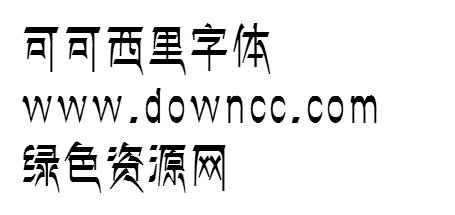
可可西里字體是在可可西里影視中較常見到的一款藏文字體,中英文都有著不錯的藝術(shù)風(fēng)格,造型精簡而獨具地域風(fēng)情,快來綠色資源網(wǎng)試試吧!
電影《可可西里》海報“可可西里”四個字根據(jù)藏文設(shè)計的。要知道海報設(shè)計以及其它正規(guī)的設(shè)計是不允許出現(xiàn)字庫里的字體的設(shè)計師需要自己設(shè)計出來專屬的字體原創(chuàng)性一致。
可可西里字體采用方正藏意字體設(shè)計而成,暫推薦該字體下載!